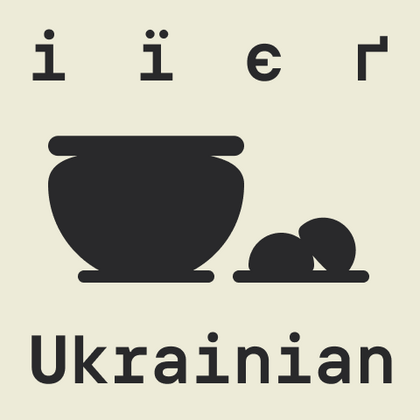
Подборка Украинских шрифтов
Такие гарнитуры незаменимы при создании контента на украинском — от официальных документов и образовательных материалов до рекламы и веб-дизайна. Шрифты на украинском языке — это гарантия корректного отображения всех специфических символов, включая буквы «і», «ї», «є» и апостроф. В коллекции TypeType каждый шрифт для украинского языка проходит тщательную проверку: тестируется отображение диакритики, межбуквенные расстояния и читаемость в разных размерах. Это профессиональное решение для дизайнеров, издателей и брендов, работающих с украиноязычной аудиторией.
Выберите подходящий шрифт с поддержкой Украинского языка. Огромная коллекция шрифтовых семейств для любых целей и задач: набор больших текстовых массивов, оформление заголовков для веб-сайтов и печатных изданий, печать на текстиле и других материалах, оформление вывесок и афиш.
Каждый из представленных шрифтов содержит Украинский алфавит. Широкий выбор символов, знаков валют и пунктуации, шрифтовых начертаний и OpenType фич позволят применять один шрифт для разных проектов. Знаки расширенной латиницы, содержащие диакритические знаки, расширят возможности использования шрифта для разных стран.
Каждый шрифт безупречен с технической точки зрения. Многие шрифты из коллекции содержат вариативное начертание, с помощью которого можно создавать уникальное начертание для проекта.
TT Polihaus — экспериментальный гротеск, который на первый взгляд кажется обычным, а затем разбирается на части, превращаясь в трафаретный узор.
TT Odellia — старостильная антиква с современным рисунком, вдохновлённая венецианскими шрифтами и классической музыкой.
TT Nooks Serif — акцидентная новостильная антиква с лёгким налётом эгоцентричности. У неё острый и твёрдый, при этом элегантный и статный характер.
TT Chocolates — изящный гуманистический гротеск сo сбалансированными пропорциями, близкими к классическим. Шрифт с приятным дружелюбным характером, который интуитивно воспринимается как что-то знакомое.
TT Nooks Script — шрифт с уникальным рисунком, который не имеет прямых аналогов.
TT Qurdisma — узкий и плотный декоративный шрифт, напоминающий причудливое растение. Вьющиеся, плавные контуры рождают растительный орнамент.
TT Dott — экспериментальный пиксельный гротеск, в котором за основу пикселя взят круг. Это пластичный и необычный акцидентный шрифт, вызывающий ассоциации одновременно с вышивкой и техно-вечеринками.
TT Supermolot Neue — технологичный модульный гротеск с футуристическим настроением и мощным функционалом. Яркость его характера сочетается с универсальностью применения.
TT Rationalist — функциональный и оригинальный брусковый шрифт с актуальным рисунком. Он универсален и подходит как для заголовков, так и для массивов текста.
TT Commons™ Classic — универсальный геометрический гротеск для широкого круга задач.
TT Runs — это выразительный шрифт, который идеально впишется в проекты со спортивной тематикой. При этом гарнитура отлично подойдет и для других современных проектов: после обновления сфера ее применения значительно расширилась.
TT Bells сочетает в себе элегантную мягкость антиквы с непростым и дерзким характером, который выражается в прямых срезах и клинообразных засечках. В основе шрифта лежит ширококонечное перо, характерное для старостильных шрифтов, создающее эти атмосферные срезы и засечки.
TT Regins — шотландская новостильная антиква с королевским характером. Яркий контраст и острые треугольные засечки придают этому шрифту строгий и властный нрав.
В TT Frantz можно найти небольшие отсылки в эстетике арт-деко, которые выражены в сильно заниженной или наоборот сильно завышенной талии у букв. Кроме того, в зависимости от положения ползунка регулировки оси, у некоторых букв изменяется закрытость апертуры.